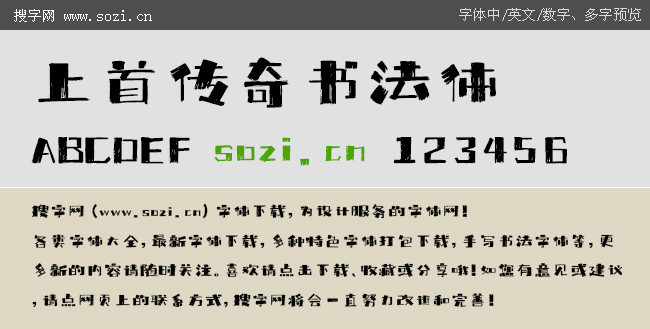
上首傳奇書法體
搜字網(wǎng)給大家提供一款上首布丁體中文字體下載,上首傳奇書法體簡體中文約6763字,字體方正工整,筆刷顯著,粗細(xì)變化強(qiáng)烈是此套字庫的亮點(diǎn),具有獨(dú)特性。適用于海報(bào)設(shè)計(jì)、包裝設(shè)計(jì)等廣告設(shè)計(jì)場(chǎng)合使用。